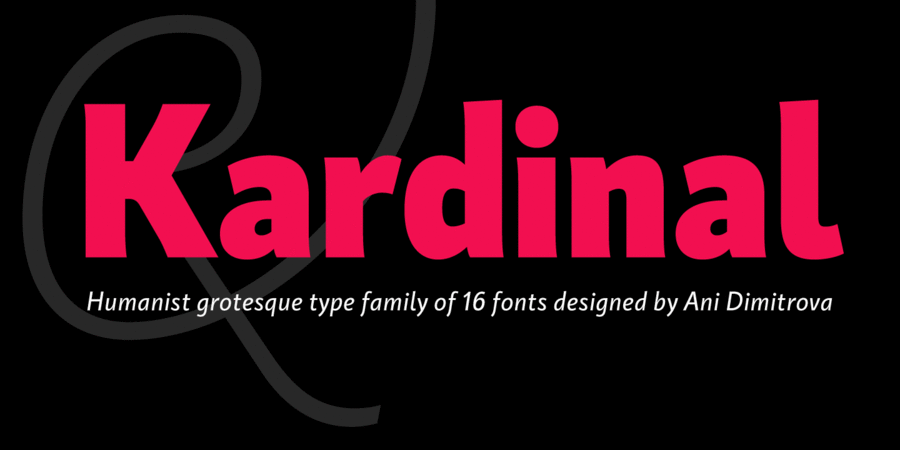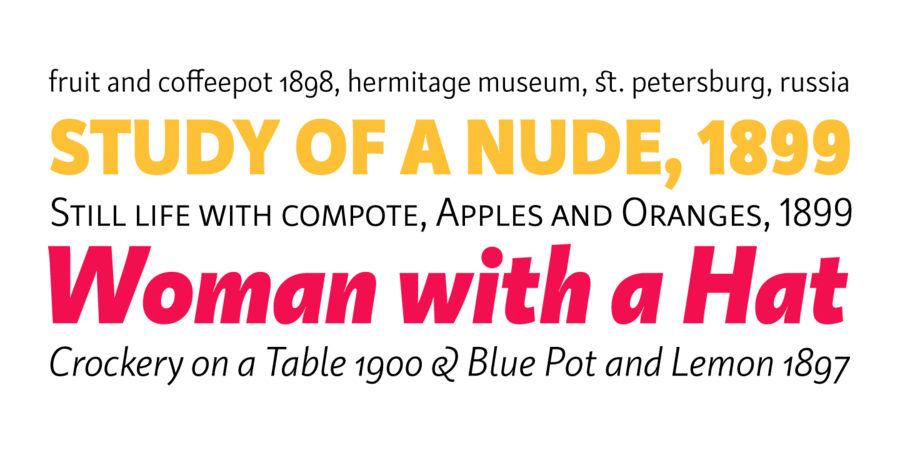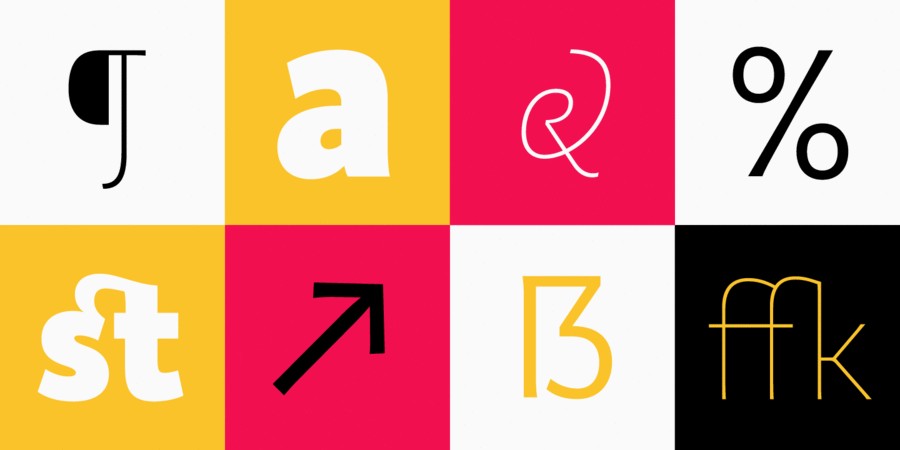
Опис гарнітури KardinalЦе гуманістичний гротеск з 16 накресленнями, від Thin до Black зі справжнім курсивом і капітеллю. Світле накреслення безкоштовне для безлімітного використання на умовах ліцензій «Десктоп» і «Веб». Шрифтове сімейство Kardinal ідеально підходить для книг і журналів, брендингу, плакатів, а також для текстів та заголовків на сайтах. Kardinal має розширену мовну підтримку, включно з кирилицею. Всі накреслення містять стандартні лігатури, пропорційні цифри, табличні цифри, мінускульні цифри, індекси, стрілки, символи валют і дроби. Конструкція знаків об'єднує чистий гротесковий стиль із гуманістичним присмаком і нотками каліграфії. Відмінною рисою шрифту є дрібні ледь помітні зарубки, що надають літерам динаміку й свіжість. Вони сприяють кращій читаності в текстах різного обсягу та створюють унікальні риси характеру. Прямі накреслення підходять для основного тексту, а курсиви мають дуже цікаве срібло набору. Різноманітність накреслень надає цій гарнітурі велику гнучкість. Знаки ретельно промальовані та ідеально підходять для екранного використання. Шрифт розробила Ані Дімітрова в 2019 році.
Особливості сімейства шрифтів KardinalХіт десятиліття:
Асоціації з сімейством шрифтів KardinalОсобистість і характер гарнітури:
делікатний, чистий, легкий, прохолодний, тонкий, сучасний, якісний, невагомий, прозорий, інтимний, крихкий, ніжний, повітряний, дротяний, худий, стрункий, ввічливий, свіжий, ясний, рівний, міський, формальний, зрозумілий, довірчий, доступний, комфортний, освічений, гуманітарний, культурний, точний, твердий, мотивуючий, помітний, яскравий